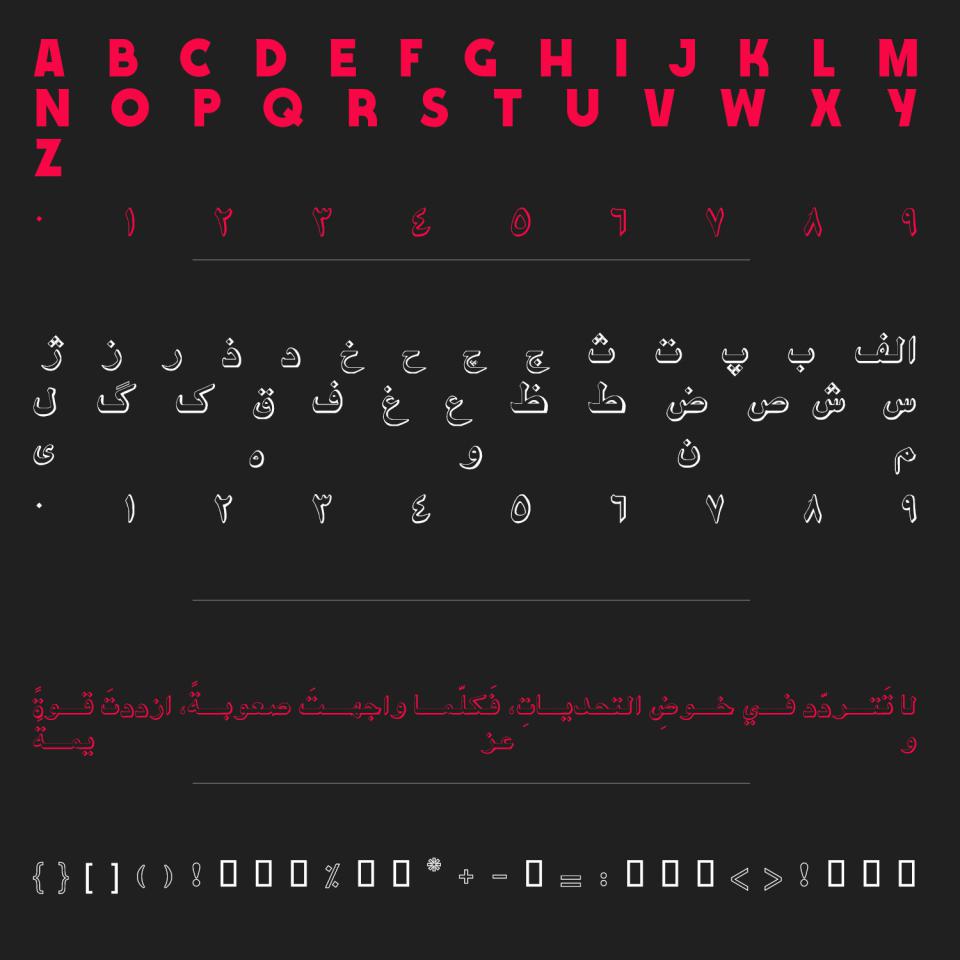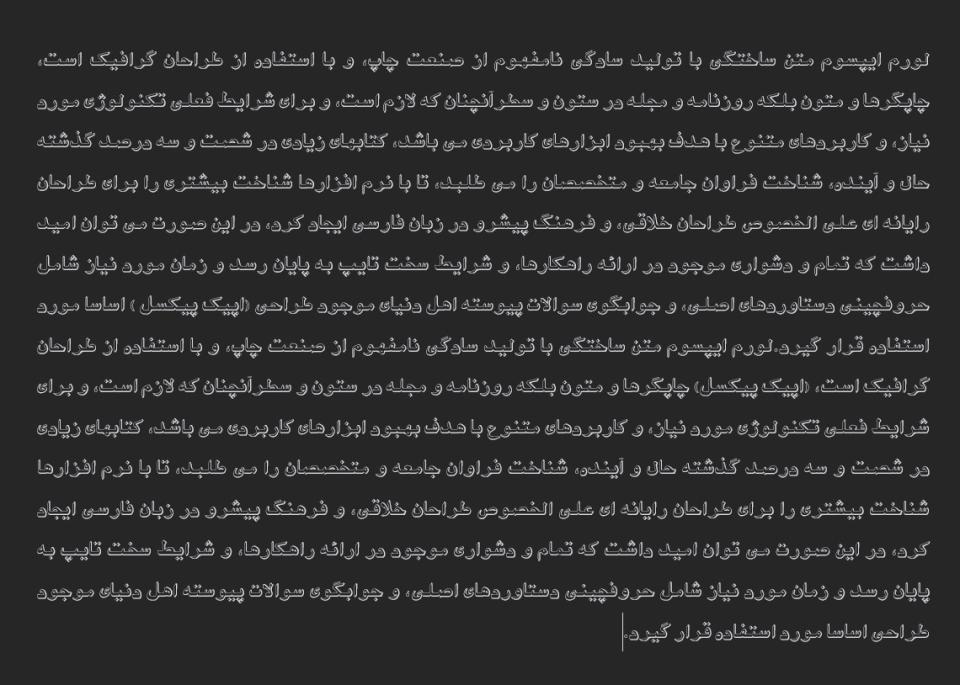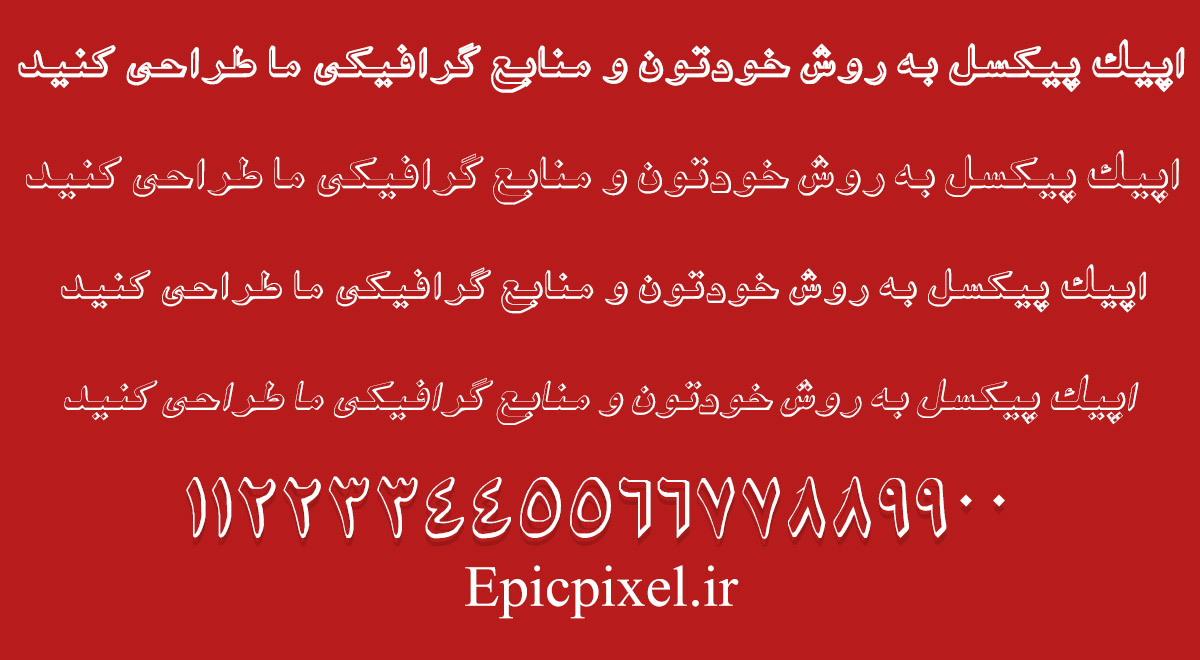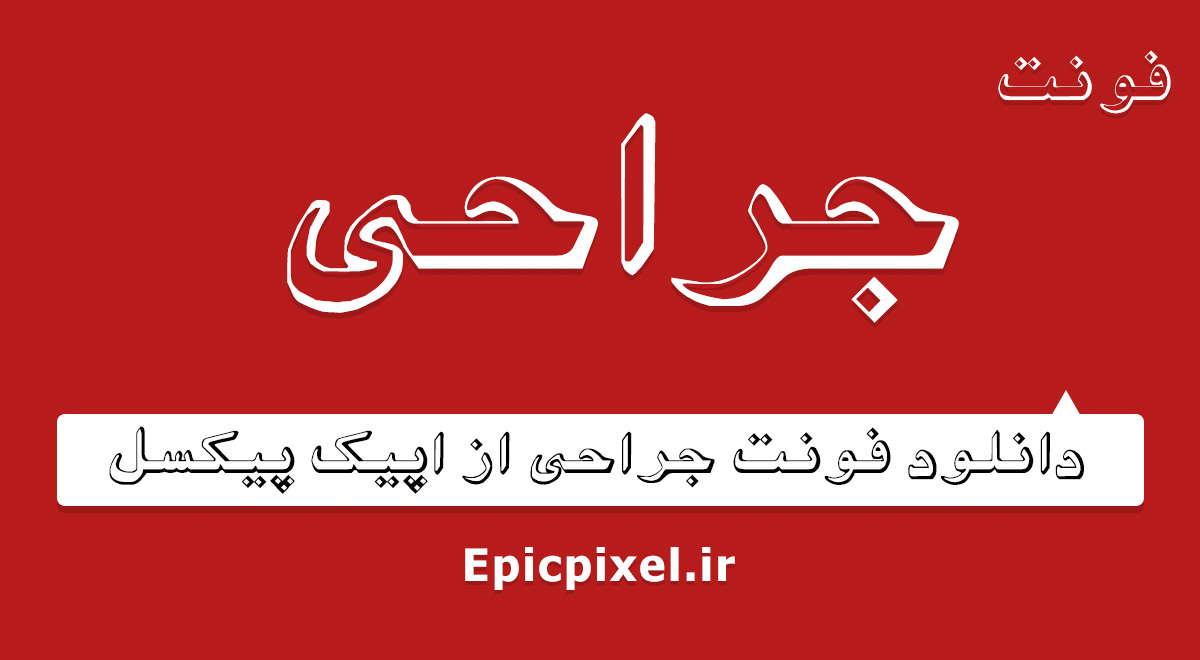
اگر به دنبال فونتی خاص و منحصربه فرد برای پروژه های طراحی خود هستید، فونت جراحی فارسی گزینه ای ایده آل است. این فونت با طراحی مدرن و ساختار هندسی دقیق، حسی از ظرافت و استحکام را به مخاطب القا می کند. خطوط این فونت به گونه ای طراحی شده اند که هم در اندازه های بزرگ و هم در متون کوتاه، خوانایی بالایی داشته باشند و به همین دلیل، برای طراحی لوگو، عناوین، پوسترها و بسته بندی محصولات بسیار مناسب است.
یکی از ویژگی های برجسته این فونت، هماهنگی بی نظیر حروف با یکدیگر است که باعث می شود متن ها روان و چشم نواز به نظر برسند. طراحی این فونت به گونه ای است که می تواند در طیف وسیعی از پروژه ها، از طراحی های مدرن و مینیمال گرفته تا طرح های سنتی تر، مورد استفاده قرار گیرد. این فونت رایگان است و به راحتی می توانید آن را دانلود و در پروژه های خود استفاده کنید. با استفاده از فونت جراحی فارسی، می توانید به طرح های خود جلوه ای ویژه و متمایز ببخشید و مخاطبان را تحت تاثیر قرار دهید. این فونت در دسته بندی فونت های فارسی خاص و جذاب قرار می گیرد.
این سبک فونت ها برای بنر های سر در مغازه هایی که میخوان فلکس کار کنند خیلی خوبه مخصوصا اینکه می تونند بعنوان فونت حاشیه دار و دور بری شده استفاده کنند.